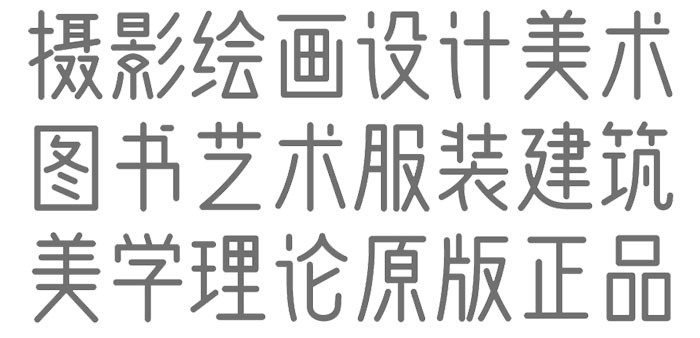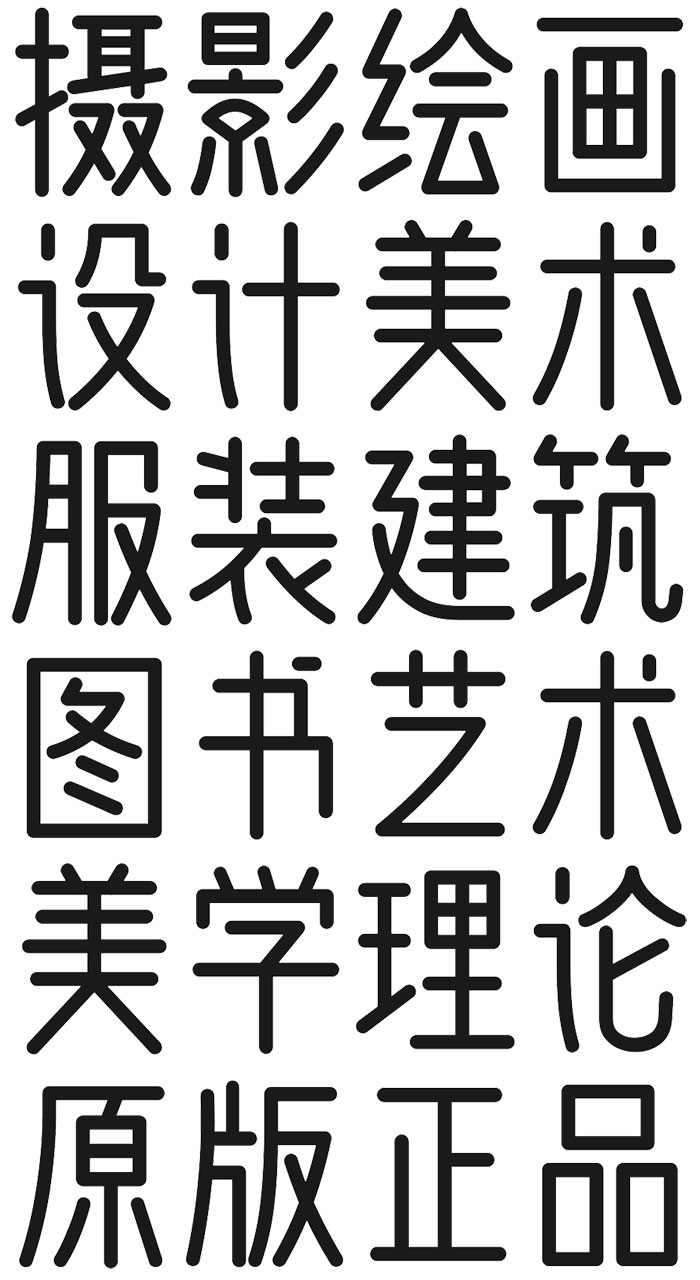
問藏書房是造字工房創始人丁一將二十餘年收藏和學習的數千本設計、繪畫、攝影、字體等藝術圖書全部捐助於問藏書房而創建。意向通過問藏書房免費借閱給對設計與藝術、美學類相關知識有興趣的同學。在各界朋友的幫助和造字工房創新資金全力支持下,投入數百萬元,將藝術與美學類書籍的藏書量增至萬餘冊,一併無償開放借閱給熱愛書籍、對審美有更高需求的朋友們,以實際行動為中國的審美教育貢獻一份綿薄之力!
適逢中華人民共和國成立七十週年,問藏書房聯合造字工房一起,以始終如一的原創精神,精心打造了一款字體產品“問藏書房”字體,在舉國同慶之際,開源給中國大陸地區一切個人與商業機構免費使用,以感謝國家給予的所有權益政策,感恩回饋一路支持正版字體的客戶和朋友!
問藏書房字體的設計整體現代簡約,中宮緊湊,視覺閱讀極具層次感,字字俊秀且呈現古雅之風,設計團隊以精心的設計賦予了漢字全新美感!字符編碼採用中華人民共和國GB2312-80字符集標準,按需添加101個漢字。共收容字數6864CJK漢字,ASCII常用字符100個。